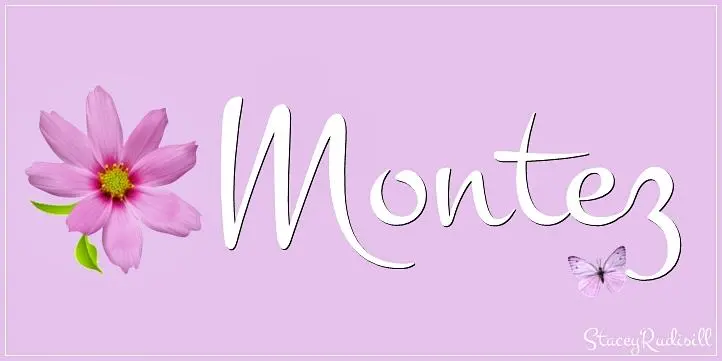
Montez font – Download Grátis
A Montez é uma fonte script inspirada nos anúncios de produtos de beleza dos anos 1960. Suas linhas suaves e deslizantes criam um tom de alegria e elegância, tornando-a perfeita para aplicações visuais que exigem um pouco de drama, “joie de vivre” ou mesmo alegria na vida. É especialmente adequada para textos grandes e médios, onde o foco é garantir uma leitura clara e suave. A Montez se destaca como uma opção ideal para design gráfico profissional e criações digitais que buscam um toque atraente de elegância e vitalidade no seu layout.